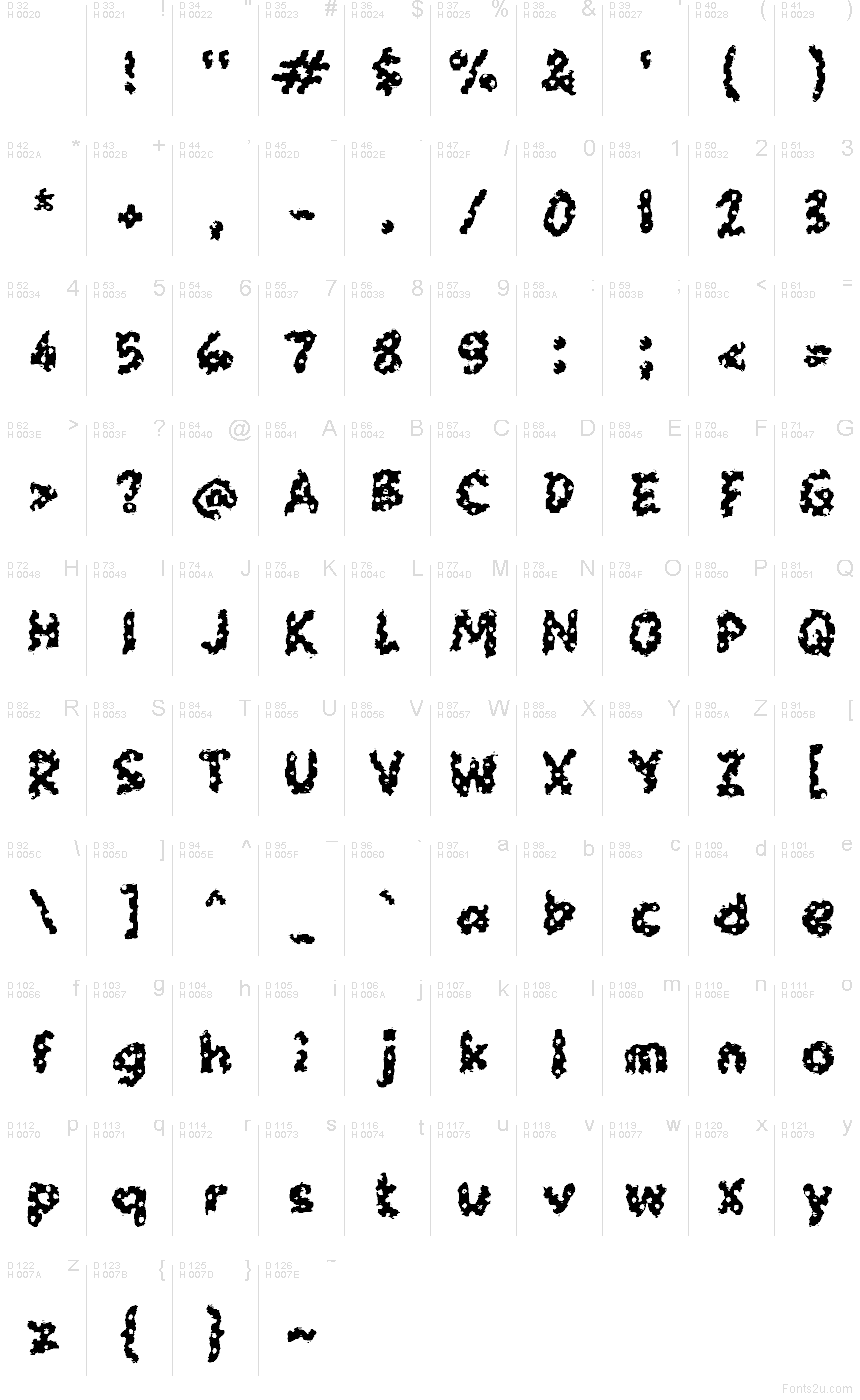
Sabadot de Wep est une police display gratuite au style « tache d'encre » brut, avec une silhouette presque fongique. Les lettres semblent gonflées, creusées et irrégulières, comme si de la peinture épaisse ou du goudron avait séché autour de trous épars, donnant à la police un rythme chaotique qui se veut plus organique qu'ornemental.
C'est ce qui rend cette police gratuite parfaitement adaptée aux affiches d'horreur, aux flyers de la scène underground, aux couvertures de fanzines, aux titres de jeux vidéo et aux identités visuelles audacieuses où les formes doivent paraître instables et vivantes. Elle excelle aussi dans les titres courts et les monogrammes : ses contours épais et ses vides en forme de cratères imposent le ton en quelques lettres seulement.